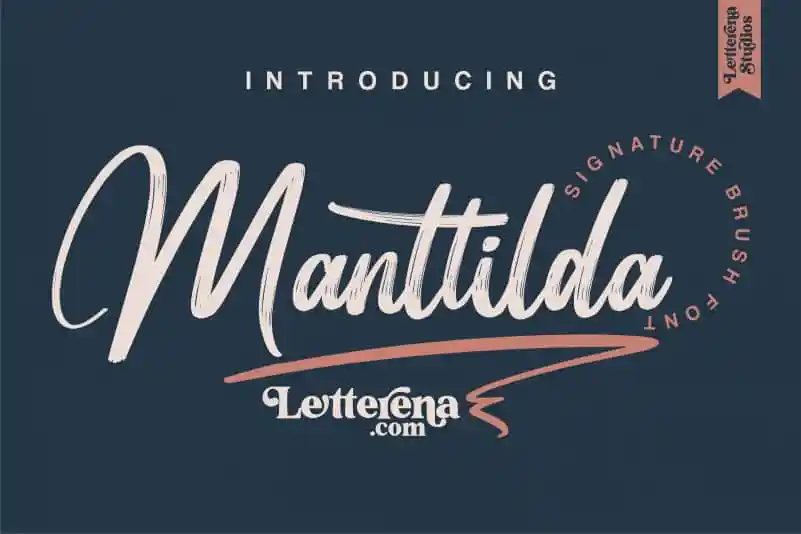
Manttilda Brush Font – Fonte Grátis
Manttilda Brush Font
A fonte ‘Manttilda Brush Font’ é uma escolha perfeita para projetos que valorizam delicadeza e elegância na mistura de letras chamadas, ideal para designers atentos ao detalhe. Devido à sua natureza romântica e escrita por um artesão da letra, esta fonte se destaca como uma opção única para diversos tipos de projetos, desde a criação de logotipos até a design de embalagens de produto. Seja para marcas personalizados em tênis ou sobre cartões de convite, o ‘Manttilda Brush Font’ promete dar um toque especial a qualquer projeto que você desenhar com ela. Suave e elegante, essa fonte é especialmente adequada para produções luxuosas, como capas de livros, embalagens de mercadoria ou até mesmo cartões de visita. Essa ferramenta de texto irá certamente se destacar em qualquer projeto que você desejar dar um toque a mais de sua arte digital.